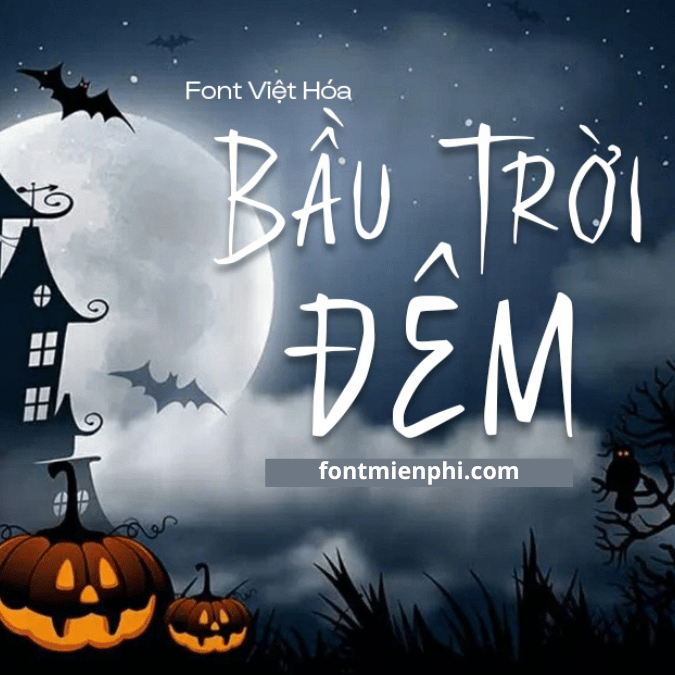
Font Việt hóa 1FTV VIP Morbid Night ,font Halloween
Font Việt hóa 1FTV VIP Morbid Night – Phông Chữ Halloween Độc Đáo, Ấn Tượng
Font 1FTV VIP Morbid Night là bộ font chữ Việt hóa đậm chất Halloween, mang phong cách ma quái, rùng rợn nhưng vô cùng nghệ thuật. Với thiết kế sắc nét, đường nét gồ ghề và hiệu ứng kinh dị, font chữ này hoàn hảo cho các dự án:
• Thiết kế poster Halloween
• Ấn phẩm kinh dị, truyện ma
• Logo, tiêu đề phim, game horror
• Trang trí sự kiện, hình ảnh MXH